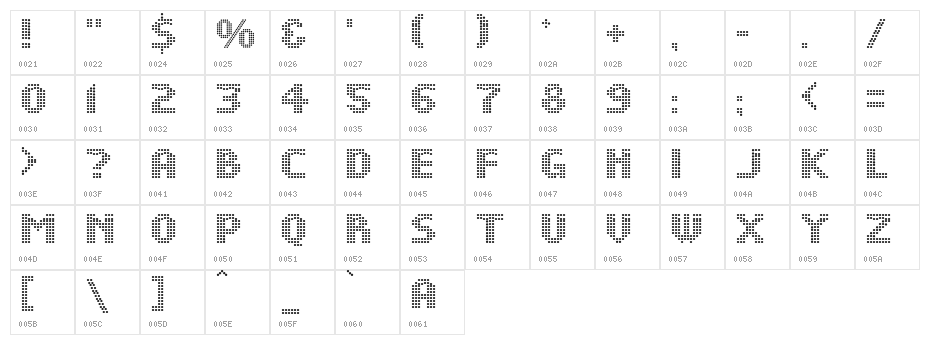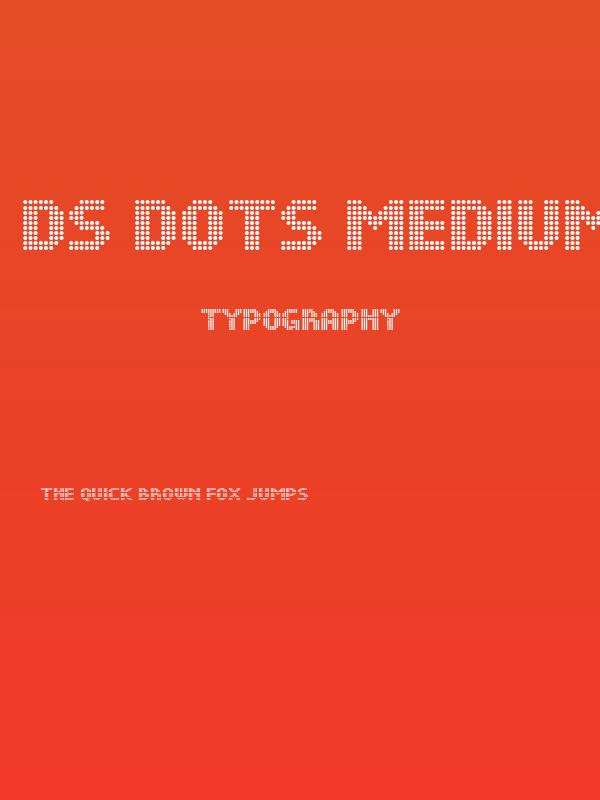
DS Dots Medium Font
✎ Dotted
| 分类 | Dotted |
| 整体风格 | Retro, Tech-inspired |
| 使用场景 | Headlines, Logos, Digital displays |
| 推荐项目 | Ideal for digital displays, retro-themed designs, tech-inspired branding, and creative posters. |